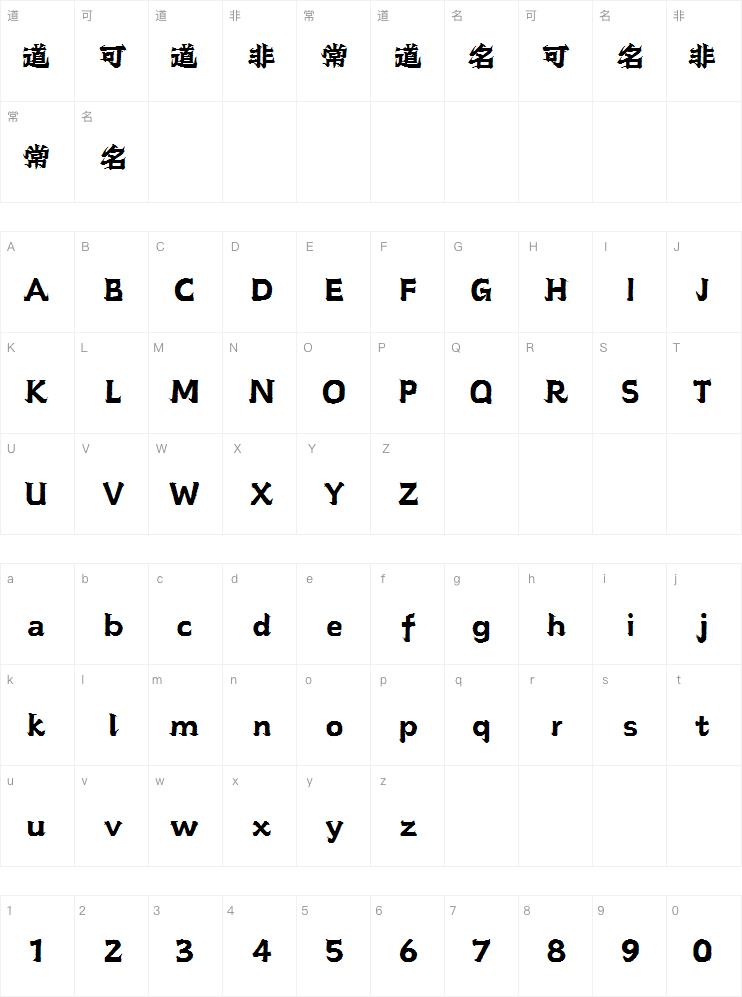
上首无极书法体
上首无极书法
上首无极书法体,取法魏碑的雄健骨力与颜体的厚重笔意,笔画粗细有致、顿挫强烈,如刀刻石般尽显苍劲力道。每一笔都蕴含 “无极” 所指的力量感与延展性,在古朴中见锋芒,于厚重中显灵动。以 “无极” 的文化哲思与传统书法的雄浑笔意为核心,融合现代视觉设计理念,打造出兼具文化深度与视觉张力的书法字体,为传统哲学表达、力量感视觉呈现提供独特的笔墨载体。适用于搭配标志、广告标语、商业广告等高端属性。